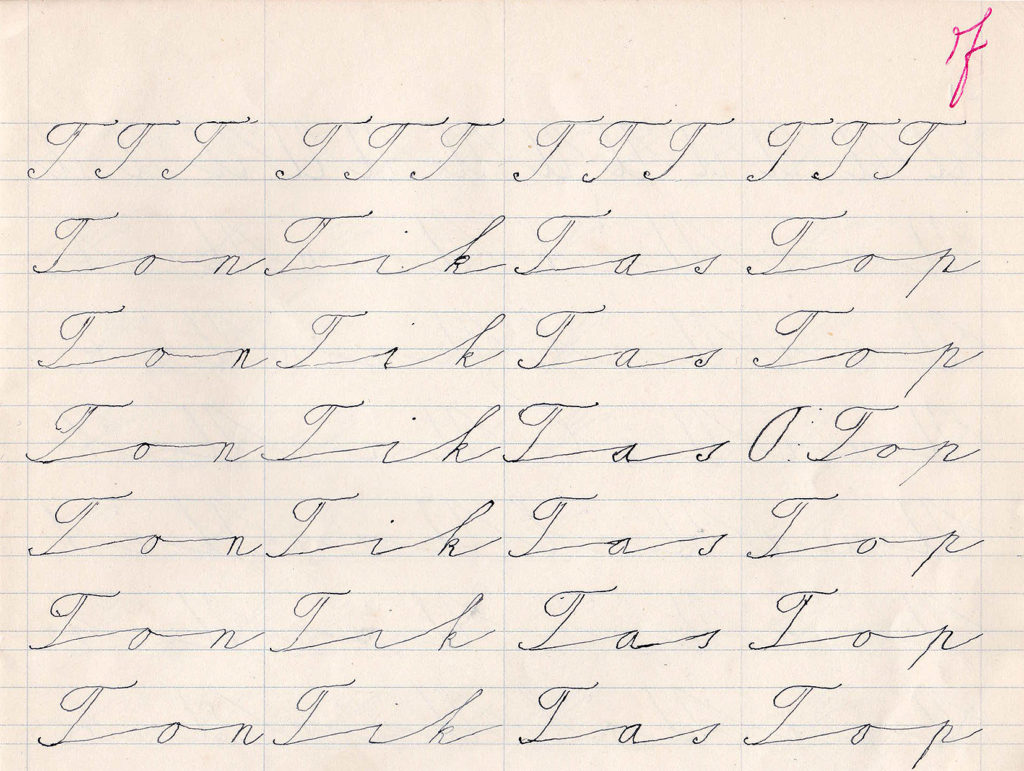
Dit is mijn schriftje uit de eerste klas, anno 1951. Zo leerde ik letters schrijven. Met de kroontjespen, tong tussen de tanden en de inktlap paraat. Eindeloos herhalen. Het zou ook misschien wel úw schriftje kunnen zijn, als u tenminste vóór de jaren zestig op de lagere school zat. Tegenwoordig leren kinderen ook nog wel schrijven, maar dan heel anders. Trouwens, schrijven we überháupt nog wel, gewoon met de hand? Of tikken we alles op de computer, met de mail, met het mobieltje? Krijgt u of schrijft u nog wel eens een handgeschreven brief? Het handschrift raakt wat verloren en dat is wel jammer en zorgelijk. Tegelijk is er toch wel een soort verlangen naar het handschrift. Er zijn diverse druklettertypen in omloop die het handschrift imiteren, of minstens ‘handschriftachtig’ zijn.
De mooiste drukletter die is ingegeven door het handschrift is de letter Zapfino, die u misschien ook wel op de computer heeft zitten. Hij is ontworpen door een groot kalligraaf en letterontwerper: Hermann Zapf, Duitser, in 2015 overleden. Hieronder zie je de naam van dit lettertype, uit 1998, zoals Zapf die kalligrafeerde. Zijn letter is zo sierlijk, zo mooi, dat hij nu als drukletter te pas en te onpas wordt gebruikt, en dan kan het ook te veel worden. Je ziet die letter op restaurantmenu’s, gevels van lingeriewinkels, suikerzakjes, noem maar op. Maar mooi blijftie!